这6种开源字体设计最常用!
一个好用的、开源的、有一定设计感和审美力的字体,对于设计师来说,将是一个非常棒的助力,可以帮助我们设计的作品好上加好,起到锦上添花的效果。今天为我们就给大家推荐6种设计最常用的开源字体,都是站酷免费字体,种类多多,风格多多,分别是:站酷高端黑、站酷快乐体、站酷酷黑体、站酷黄油体、站酷小薇logo体、站酷文艺体,都会让人觉得眼前一亮。接下来我们就一起来看看站酷免费字体里的这6种开源字体设计最常用的详细内容吧!
1、站酷高端黑
站酷高端黑就和他的名字一样,看起来就比较高级,很有设计感,是集合了众多优秀设计师的智慧及力量合力完成的,有着非常鲜明的特色,由于他的字重、字怀等方面的因素,我认为站酷高端黑这个字体会比较适合制作标题或者一些简短的文字时使用。最最重要的是,站酷免费字体提供的这一款站酷高端黑字体是一个完全免费的、可商用的开源字体设计,可以帮助我们解决很大一部分设计字体却要花钱才能商用的烦恼,省时省力又省心。
2、站酷快乐体
站酷快乐体可以说是站酷免费字体中的一款可爱有趣、活泼俏皮的个性字体,有着很强的设计特色,让人看了心情都有可能会由阴转晴。我个人认为站酷快乐体很适合应用在创建网页标题、促销主题、产品包装设计等方面。而且,由于他活泼可爱的字体设计,加之对所有人都免费甚至是商用的版权许可,在很多综艺节目中我们也可以看到这款字体的影子,可以说站酷快乐体是一款很了不起的一款免费开源字体。
3、站酷酷黑体
站酷酷黑体这款字体由著名设计师胡晓波发起设计,整个字体的字形笔画非常粗犷有力、中宫饱满,有一种厚重感,很适合标题类字体的创作,可以使文字与文字之间的排版组合更加醒目好看。而且,这款字体非常注重细节,在笔画细节处做了修饰,使得整个字体的设计感得以增强,看起来也更加精致,是一款非常不错的站酷免费字体资源。
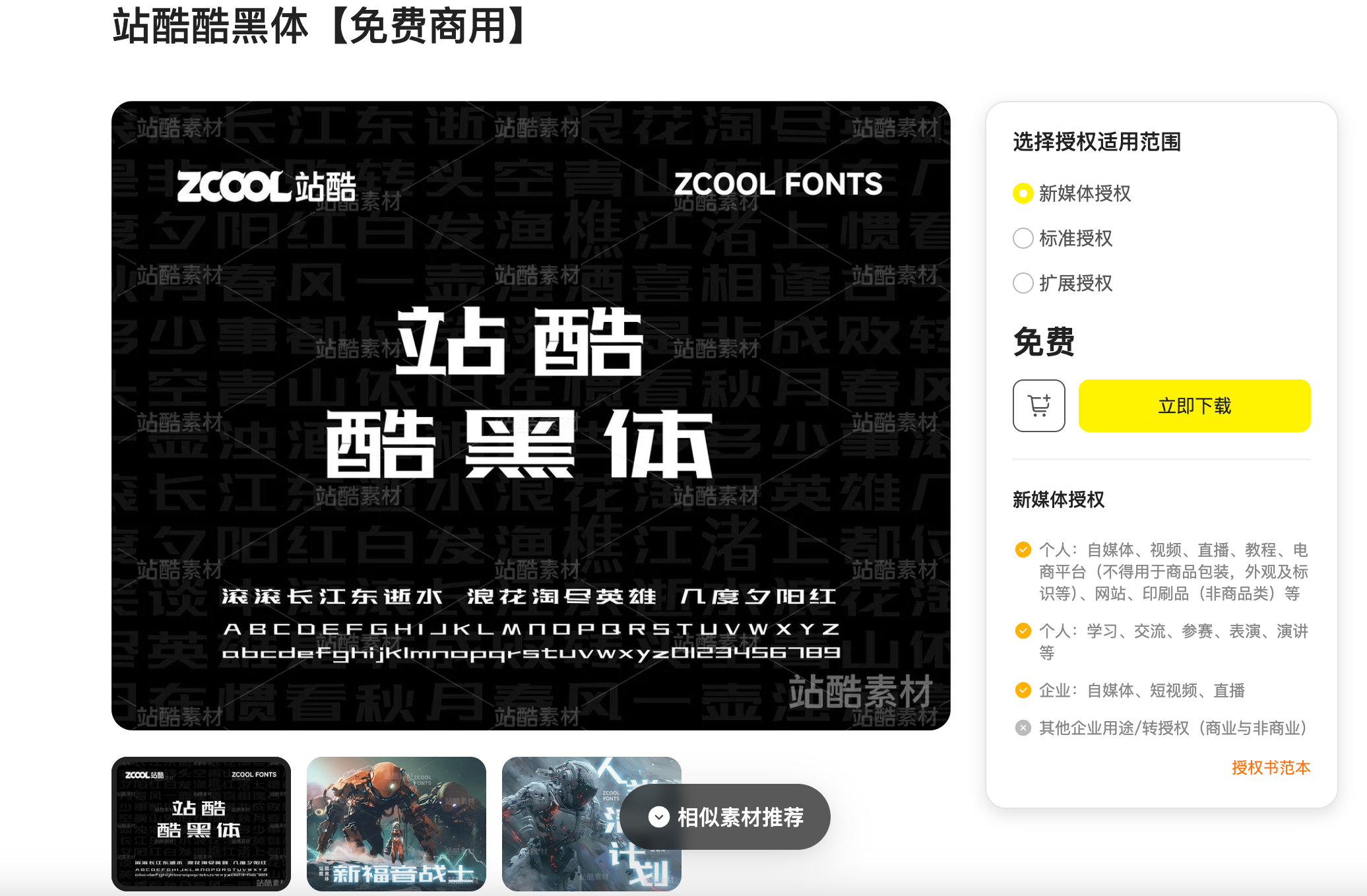
4、站酷黄油体
站酷黄油体可以说字如其名,他的整个字体设计就像黄油一样圆润,甜而不腻,就我个人来说,会更加倾向于在食物或者一些需要营造出甜蜜氛围的设计中使用这一款字体,是一款很有设计感的站酷免费开源字体。
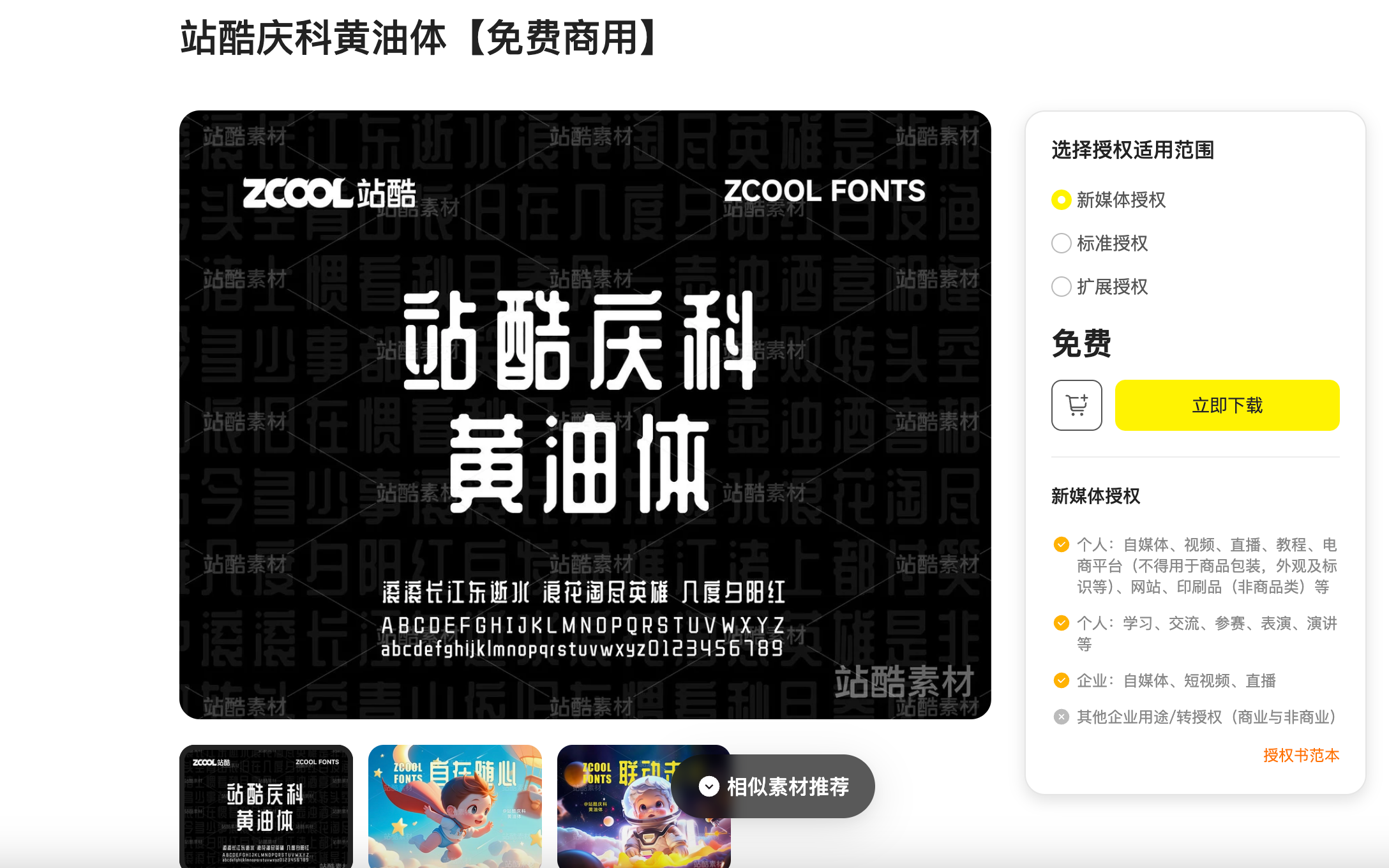
5、站酷小薇logo体
站酷小薇logo体是一个专为Logo设计而生的站酷免费字体,有效填补了免费字体中没有Logo字体设计的空白。这款字体设计笔画浑厚,线条流畅,结构简洁大方,设计感十足,加之对字体进行了变形设计处理,非常有趣味性,是一款很不错的站酷免费开源字体设计。
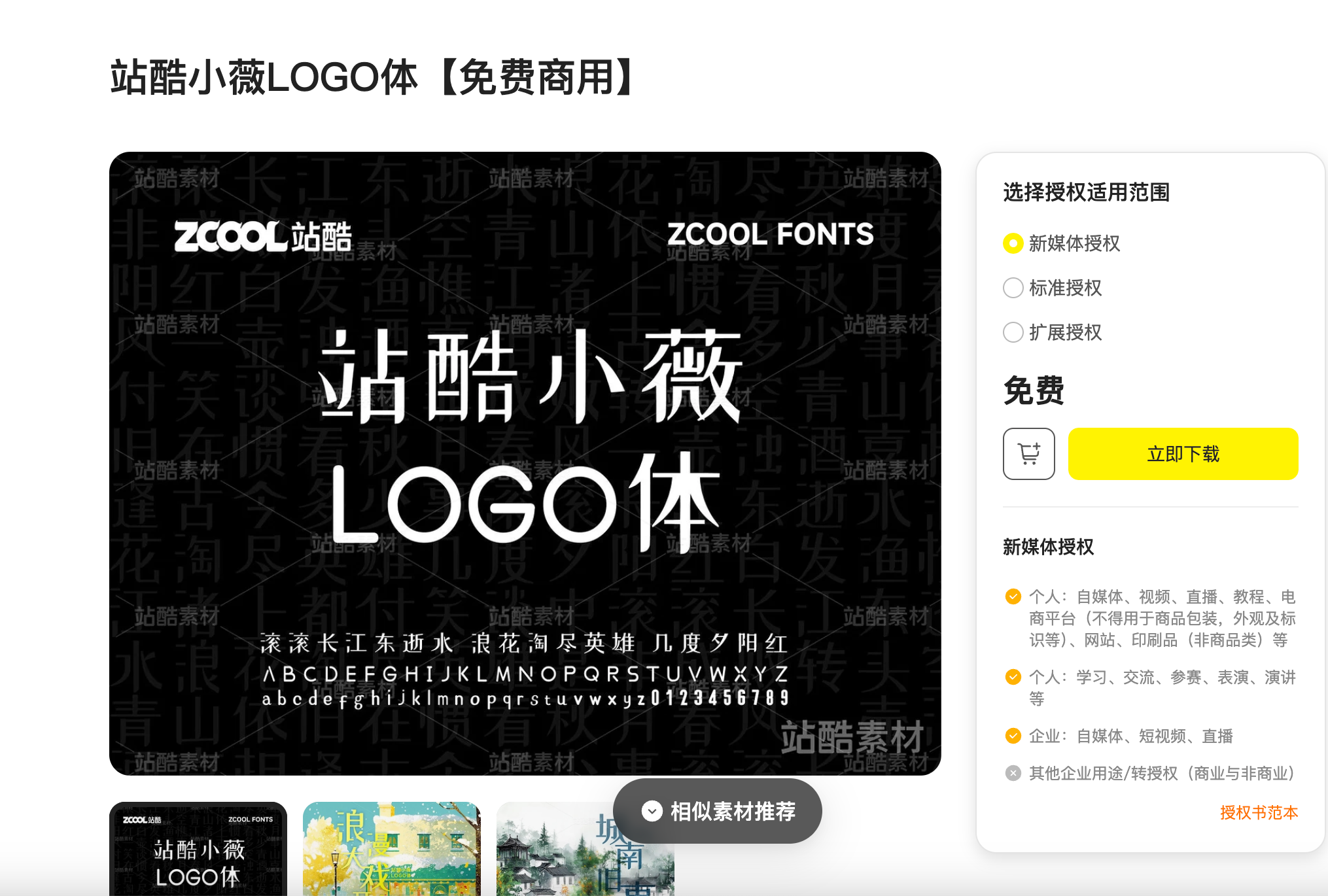
6、站酷文艺体
这是一款有点小清新、同时又文艺范十足的站酷免费字体,简洁有力、新颖独特。相对来说会比较适合制作广告、海报、电商或者banner等设计中,无论是作为标题还是正文内容,都会给人带来一种舒适的视觉享受。他是支持所有人免费使用的,商用也没问题。